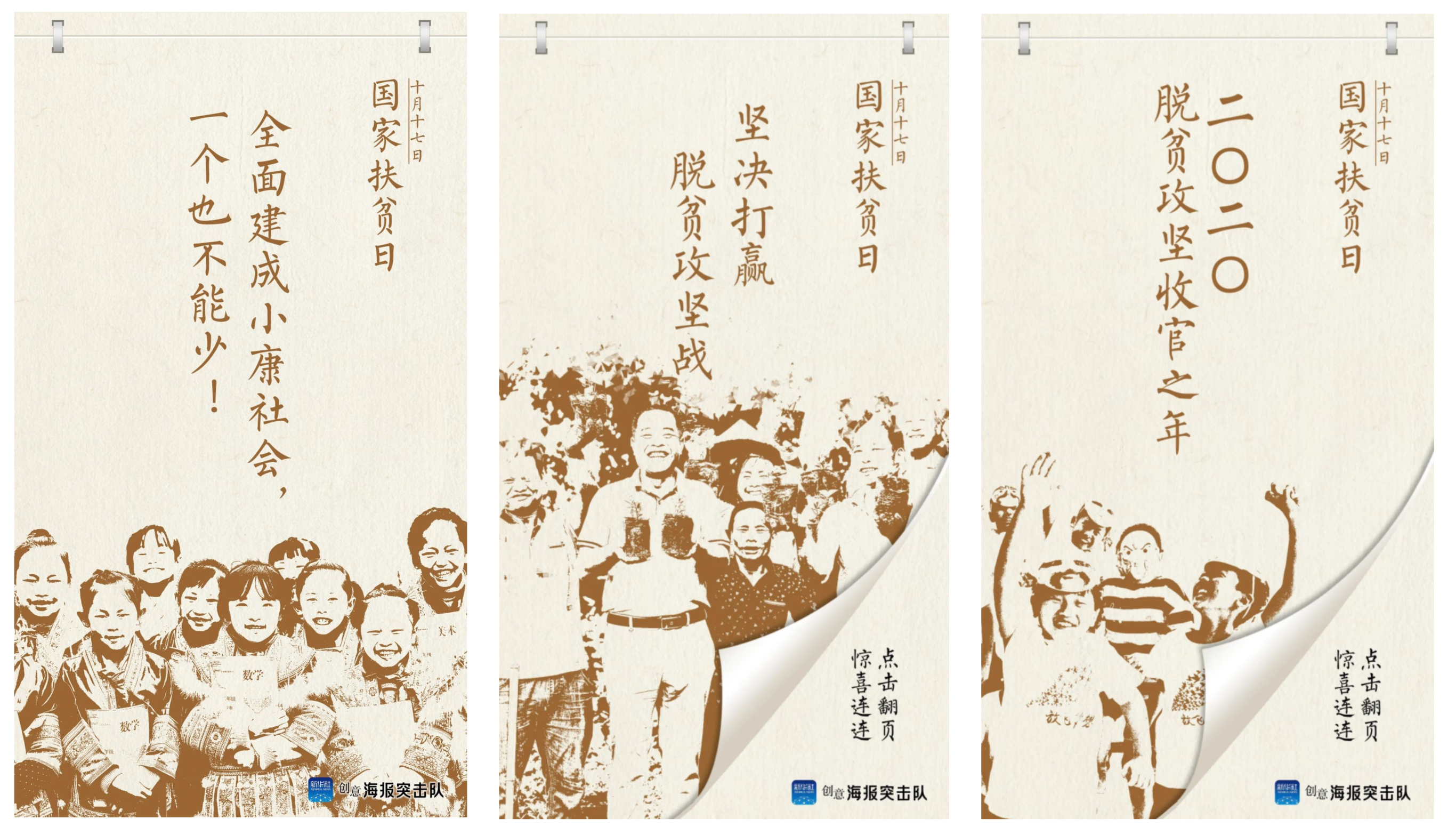
方正墨韵体家族
方正墨韵体的创作初衷是设计一款“有东方气韵的现代字体”,满足当代追求的东方美学基因、极简的现代气质和生活哲学。适用于东方文化和国潮类的竖屏短视频、自媒体、平面广告、产品包装、纸媒书籍的标题和内文。
方正墨韵体
方正墨韵体是一款具有东方气韵的现代字体,在创作之初,设计师便希望这款字体能够呈现当代的东方美学基因、极简的现代气质和生活哲学。历时5年,经过反复推敲、不断完善,这款传统与现代有机结合的字体正式发布。
⊙ 字型特征
方正墨韵体擢取小篆的字形结构和笔形特征,并搭配现代圆体的设计风格,希望将小篆这种在中国存在超两千年的文字类型,以一种全新的现代字体设计形式传播,使其为现代人所熟知。字体秉持着简单流畅的设计美学理念,采用简洁的流线设计,字体的笔触厚度均匀、粗细统一,字形修长、笔头圆润,重心上提、上紧下松,在古风墨色中书写东方气韵。
两种不同字重的粗细设计
两种不同字重的笔画部件设计
方正墨韵体 Light
方正墨韵体 Regular
⊙ 排版效果
作为一款具有东方气韵的现代字体,方正墨韵体竖排时具有很强的整体感,颀长的字体造型符合读者竖向阅读的视觉动向,传递一种简静柔美、舒适高雅的文本气质。
⊙ 应用呈现
方正墨韵体适用于具有东方文化特性,以及国潮类的竖屏短视频、自媒体、平面广告、产品包装、纸媒书籍的标题和内文。